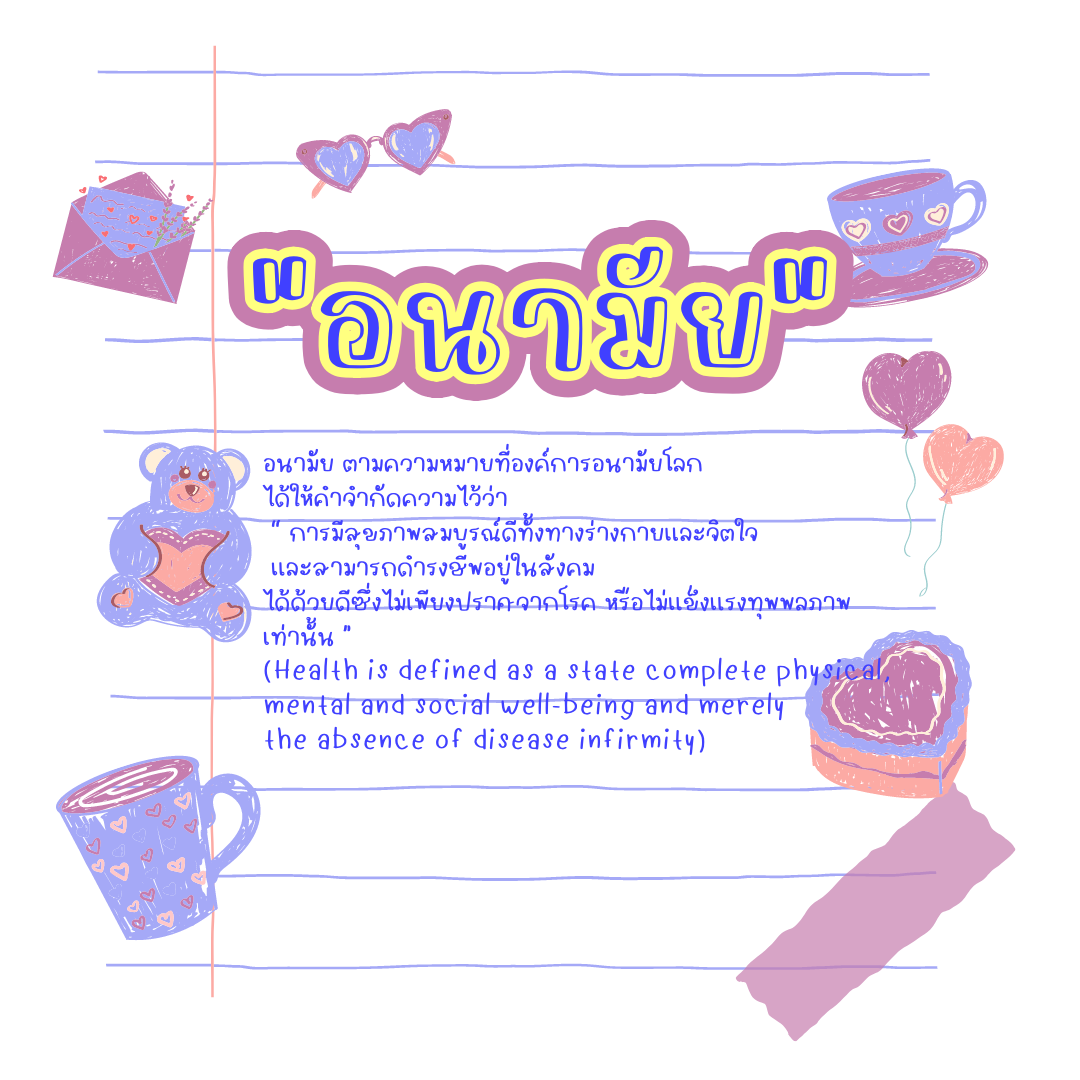
นูร่าฟาร่า (Nura fahra)
ฟอนต์ลายมือตัวโปร่งและตัวเรียบๆ สองตัวนี้เกิดจากการเขียนฟอนต์ตัวเดียวกัน  ฟอนต์มีด้วยกัน 5 น้ำหนัก คือ บาง ปกติ หนา  ตัวโปร่งขอบทึบ กับขอบโปร่ง นูร่าราดาเปิดให้ใช้ฟรีส่วนตัว น้ำหนักบาง น้ำหนักโปร่งทึบ โปร่งบาง นะคะ